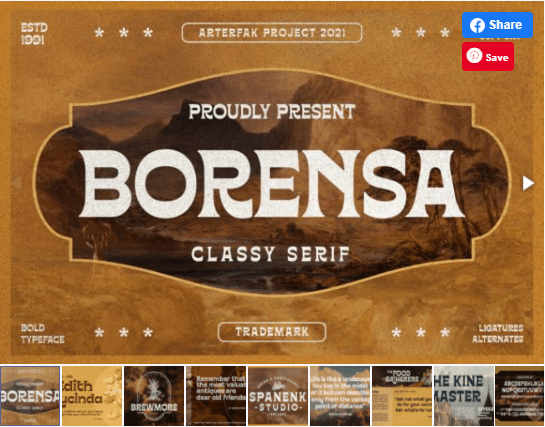
Borensa Font
Borensa - это дисплейный шрифт с толстыми буквами, жирным шрифтом в стиле ретро. Этот впечатляющий шрифт имеет буквы уникальной формы, и в результате он легко сочетается с широким спектром творений, требующих особого подхода.